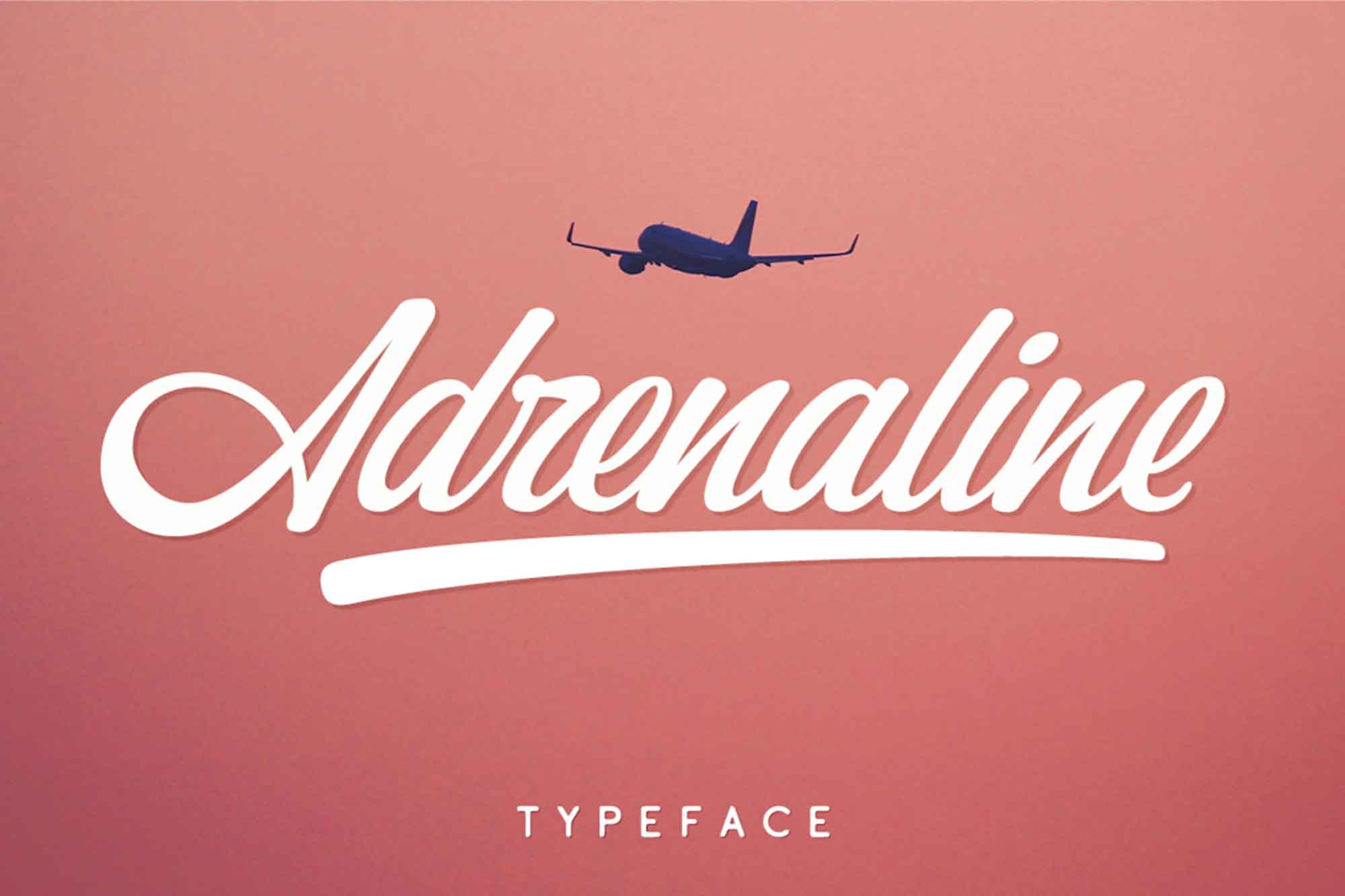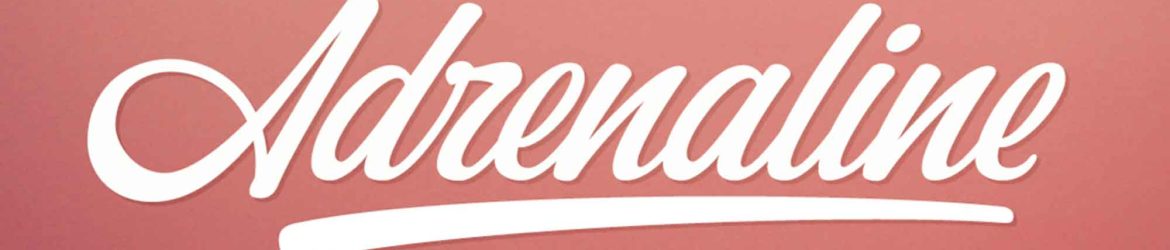
Adrenaline Script Font – Download Grátis
O ‘Adrenaline Script Font’ é uma fonte de escrita incrivelmente elegante que remonta aos maestros da escrita do século XVII e XVIII. Suas curvas exageradas e detalhes elaborados, conhecidos como swashes, que se estendem dos serifs, são a característica mais distintiva e memorável desta fonte. Suas curvas arredondadas e sua elegância romântica são perfeitas para uso em assinaturas de convites de casamento, capas de livros de romance e em qualquer design que deseje soar mais histórico e moderno. Embora seja uma fonte de alta qualidade, deve ser tratada com cuidado para evitar que seu uso extenso em grandes quantidades de texto possa transformar seu design em algo semelhante à Declaração de Independência. No entanto, a Adrenaline Script é uma fonte que nunca sairá de moda e sempre terá um lugar especial em designs que desejam um toque único e elegante.